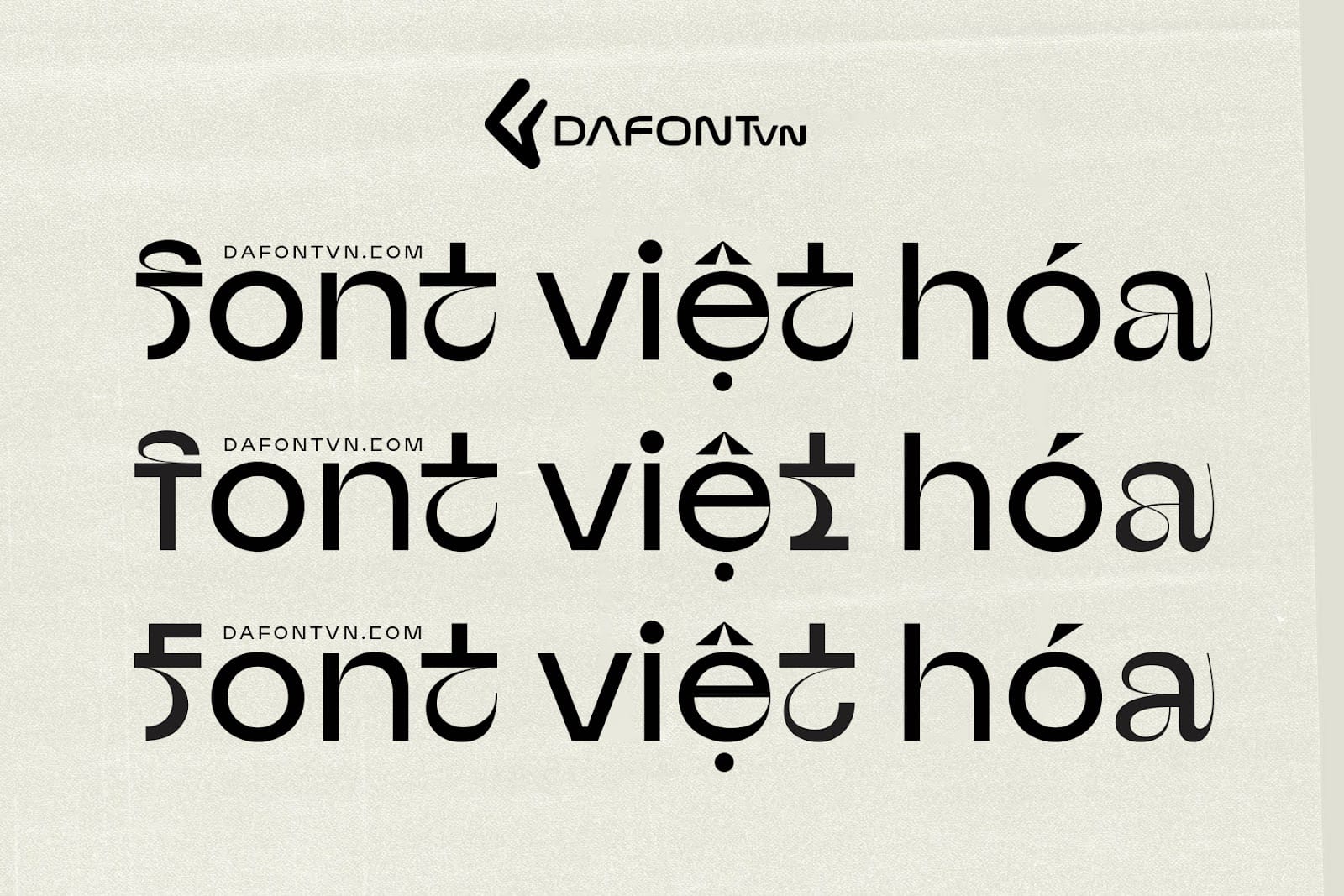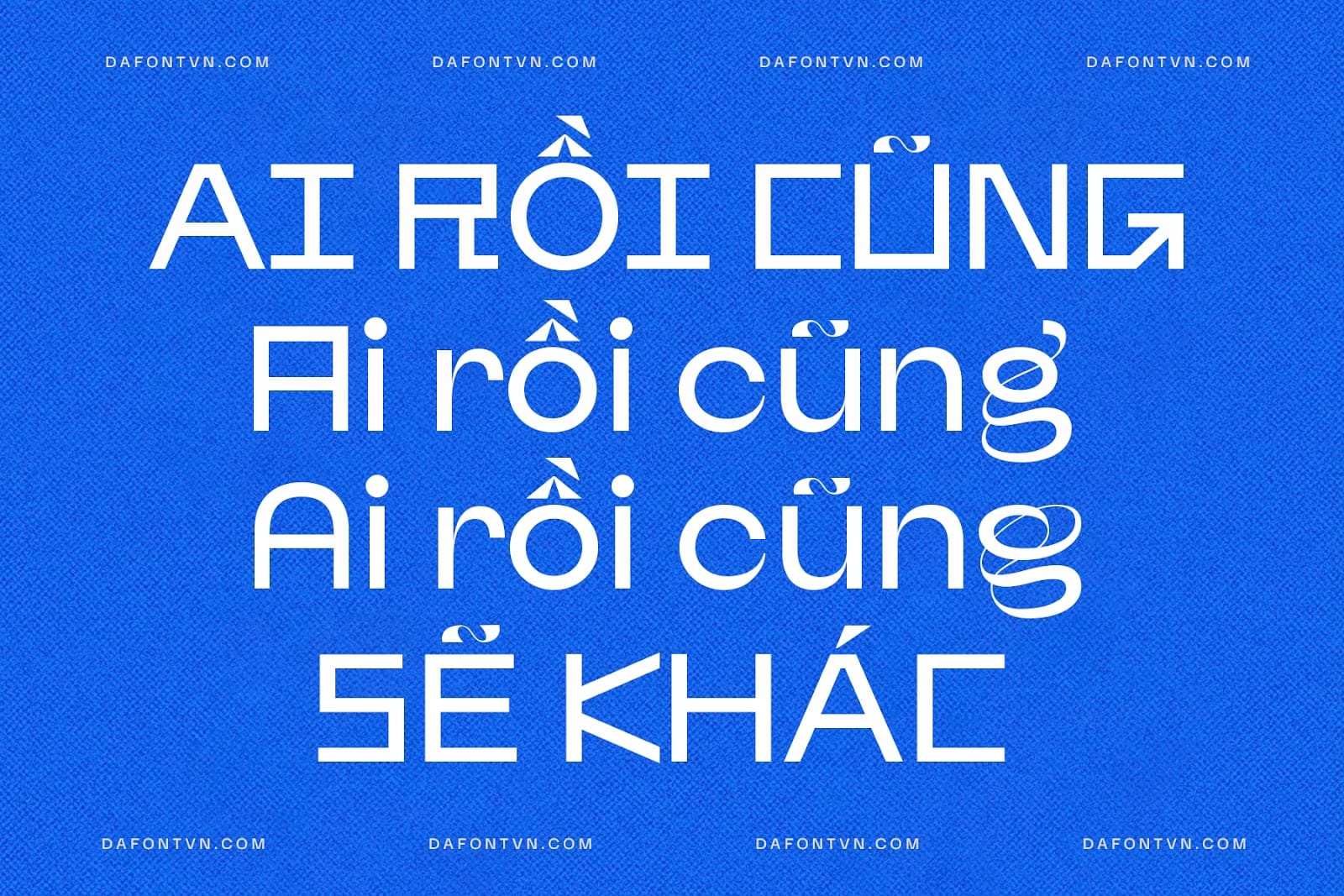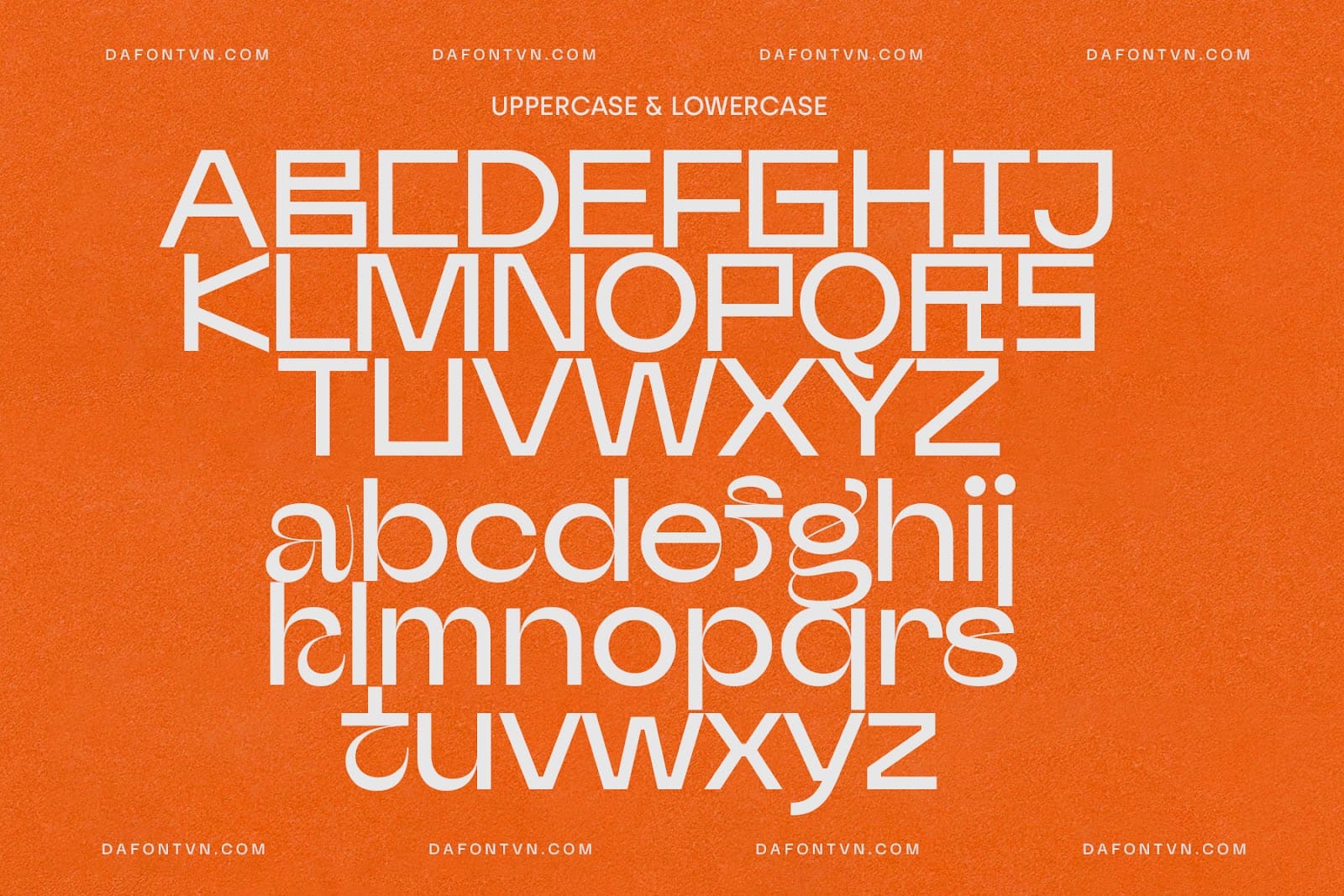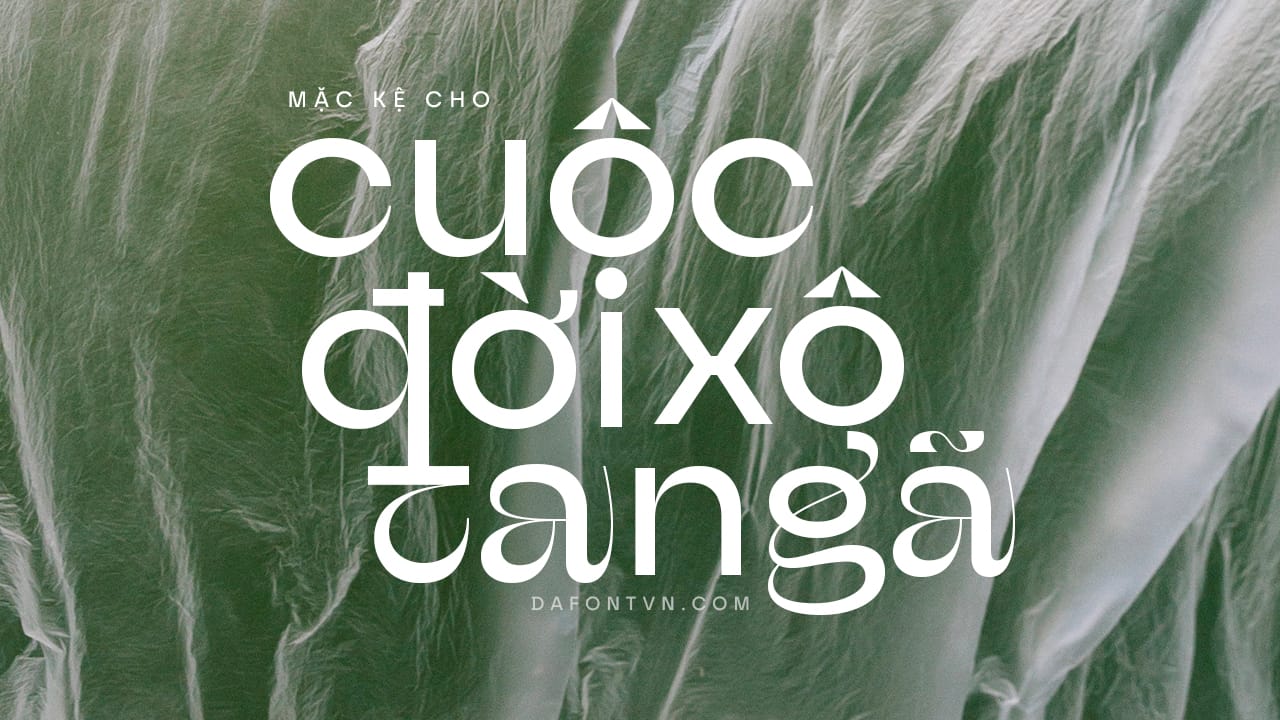
Afronaut Typeface là một kiểu chữ vô cùng ấn tượng được lấy cảm hứng từ kiểu chữ Latinh và Ả Rập. Các hình dạng hình học hoạt động tốt và tương phản với các yếu tố tròn, mịn. Font được thiết kế với các dấu ngang để tạo ra kiểu chữ giống như sự pha trộn giữa: chữ viết tiếng Ả Rập bản địa, kiểu chữ hiện đại của tương lai và một số chữ cái đặc biệt.
Afronaut với các ký tự viết hoa mang cảm giác cứng cáp, vuông vức, trong khi đó các ký tự viết thường đặc biệt hơn với các nét được thiết kế lạ mắt, ngoài ra một số ký tự khác cũng được tác giả thiết kế ấn tượng, bạn có thể sử dụng các ký tự này trong bảng glyph.
Afronaut phù cho nhiều mục đích khác nhau như xây dựng thương hiệu, tiêu đề, tạp chí, typo, bìa sách… hoặc bất kỳ thiết kế nào cần một font chữ lạ mắt, đẹp và hiện đại.
Font Afronaut Việt hóa đầy đủ, kerning, chỉnh sửa lại một số dấu và ký tự.